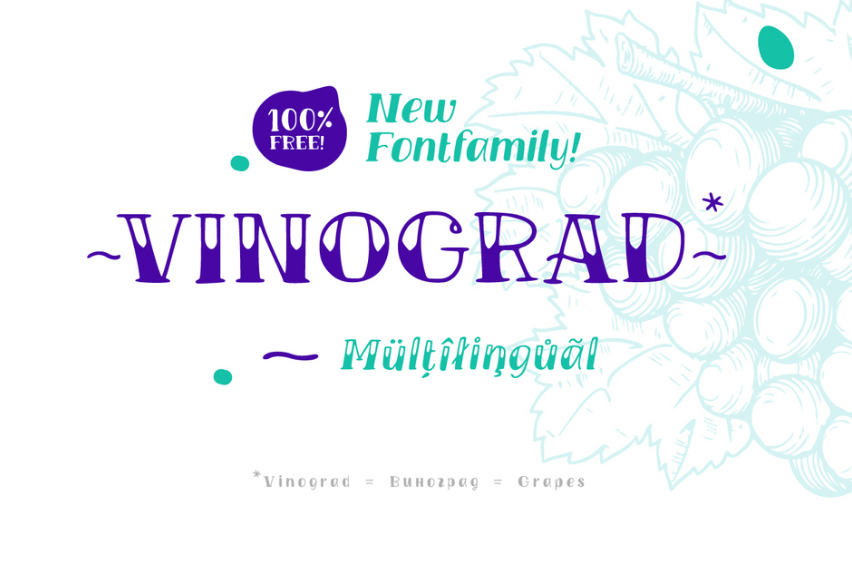
Introduzimos a TM Vinograd! Vinograd TM é uma família de fontes que reflete a elegância do estilo de escrita à mão. Desenhada gratuitamente pelo Typemate, esta família foi criada para todos os amantes do design que buscam uma solução única e distintiva. Vinograd TM se destaca como uma fonte de display, perfeitamente adaptável a diversos objetivos de design. Essa familia inclui mais de 600 glifos e duas estilos: Inscrição e Regular. Suas linhas fortes e contrastes aguçam sua versatilidade para diferentes aplicações, como cabeçalhos, logotipos, embalagens, livros infantis e revistas, bem como gráficos em camisas. A TM Vinograd Font Family também oferece extensão do alfabeto cirílico e latino. Vinograd TM é perfeito para qualquer projeto que busque um toque diferenciado sem comprometer a legibilidade. Seja você um designer de editoriais, criador de logotipos ou artista gráfico, esta fonte será uma escolha inteligente para expressar seu estilo único e criar design impecável.